1、替换法
替换法是在统一形态的文字元素加入另类不同的图形元素或文字元素。其本质是根据文字的内容意思,用某一形象替代字体的某个部分或某一笔画,这些形象或写实或夸张。将文字的局部替换,是文字的内涵外露,在形象和感官上都增加了一定的艺术感染力。
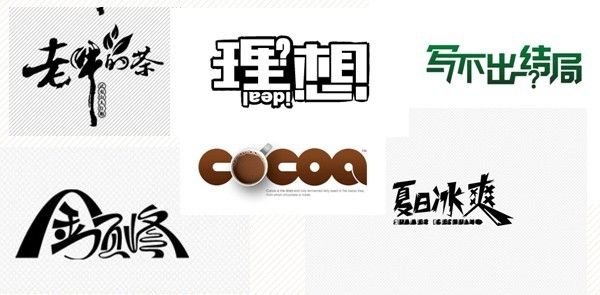
2、共用法
“笔画公用”是文字图形化创意设计中广泛运用的形式。文字是一种视觉图形,它的线条有着强烈的构成性,可以从单纯的构成角度来看到笔画之间的异同,寻找笔画之间的内在联系,找到他们可以共同利用的条件,把它提取出来合并为一。
3、叠加法
叠加法是将文字的笔画互相重叠或将字与字、字与图形相互重叠的表现手法。叠加能使图形产生三度空间感,通过叠加处理的实行和虚形,增加了设计的内涵和意念,以图形的巧妙组合与表现,使单调的形象丰富起来。
4、分解重构法
分解重构发是将熟悉的文字或图形打散后,通过不同的角度审视并重新组合处理,主要目的是破坏其基本规律并寻求新的设计生命。
总之,平面图形设计的目的是人与人的交流,作为设计者,学习运用符号学工具,会使设计更加有效。在平面设计如此繁杂的今天,把文字图形化运用到设计中,才能使作品具有强烈的视觉冲击力,更便于公众对设计者的作品主题的认识、理解与记忆。
5、俏皮设计法
把横中间拉成圆弧,角也用圆处理,这个方法还有重要一点就是色彩,字体处理上加上色彩的搭配才能作出好的俏皮可爱字体。
6、尖角法
把字的角变成直尖、弯尖、斜卷尖;可以是竖的角可以是横的角,这样文字看起来会比较硬朗。
7、断肢法
把一些封合包围的字,适当的断开一口出来 ,或把左边断一截,或右边去一截。注意:要在能识别的情况下适当断肢。
8、减细法
所有字体横和竖变细。
9、错落摆放法
把左右改为左上左下,上下排,或斜排就是一边高一边低,让文字错落有致排列。
10、方方正正法
把所有字体的弯全改成横平竖直,四四方方的。
11、卷叶法
把所有字的最左或最右横或竖或点全卷起来,像浪花一样,此法,一般是找到一个点或线后转曲,用最下面或最左边或最右边的两个点向一边拉,以加节点的方法拉成一个圈,然后把他转成倒圆角后,留着最后面的两点,慢慢删除中间的节点。
12、横细竖粗法
选定个字体后,把横比划减细竖比划加粗。类似传统宋体字,横细竖粗撇如刀。
13、上下拉长法
把字变细,然后上下拉长,类似条形码的感觉。
14、结构转变法
可以说是代替法的一种,把竖或横线或折换成其他比划。
15、照葫芦画瓢法
先画一个几何图形,方形或矩形或星形,然后把字放进去,照几何图形路线制作字体。
16、画龙点睛法(或一点拉长法)
算是拉长法的一种,找到标志中的一个点或线作为重点把他拉长,使得处理好的字体,再加一笔更是画龙点睛之作。
17、洋为中用
大家都知道,我们使用的汉字成千上万,个个不同,而西方使用的拉丁字母,大写加小写再加数字标点符号乱七八糟加起来也就一百来个,在数量上和我们汉字差距很大。这就造成了被设计出来的英文字款比中文要多得多。
面对字库里面多如牛毛的英文字体,大家是否曾经对他们视而不见或匆匆带过,其实那里面蕴藏着西方设计师的无限创意,而作为汉字的设计者,我们可以好好利用这些创意,其实方法很简单。
第一步:到字库里找几个特别点的英文字体
第二步:找出这些字体的笔触和特征
第三步:把这些特征运用到中文字体设计中去吧
依此类推,可以做出更多的字体设计。